Du majestueux au trivial
Pour l’Égypte des premières grandes dynasties à la structure gouvernementale s’ajoute celle du religieux, il est nécessaire de transmettre les ordres et les lois, de contrôler les taxes, de commander des bateaux de céréales ou de granit.
L’écriture revêt une importance nouvelle. Elle est l’outil de l’accroissement de la production, voire de l’efficacité administrative. Le Hiéroglyphique majestueux des temples est un bel organe de propagande, il semble pourtant, ce qui est regrettable, qu’il ne convienne pas aux besoins triviaux de la comptabilité et de la diffusion de décrets.
La fiscalité ne s’immortalise pas systématiquement sur les murs. Il est nécessaire de la conserver autrement, en utilisant des supports aussi légers que les taxes sont lourdes.
Ce qui implique une première étape de simplification qui fera passer l’écrit du dessin soigné au symbolique explicite. Le résultat reste lisible par les scribes et le devient pour un grand nombre de nouveaux lecteurs : administrateurs, guerriers, commerçants, prêtres secondaires, chefs de chantiers, serviteurs méritants.
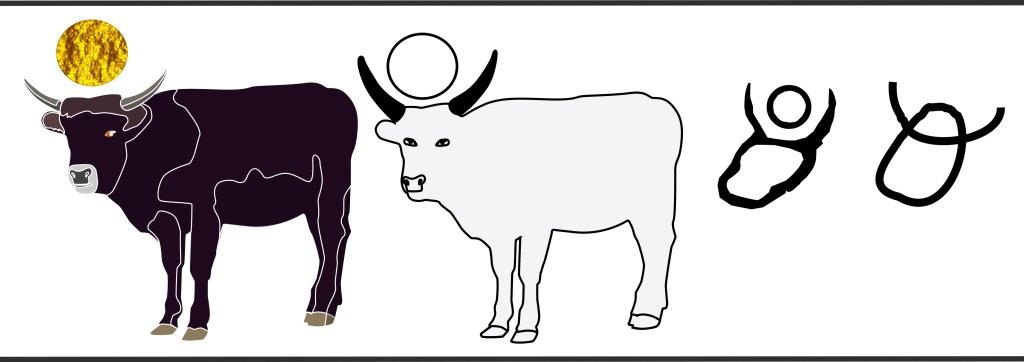
Des artistes aux besogneux
Plus de lecteurs, cela impose un surcroît de production que l’on satisfait en passant du codage en dur à une syntaxe douce, qui sera inscrite sur les murs, les tablettes et les papyrus.
Cela ne s’est pas fait sans heurter certaines sensibilités.
Le détournement des artisans de pointes et de burins, ces experts funéraires qui gravent la pierre ou enluminent les murs des temples, tombeaux et sarcophages, est contre-indiqué si l’objectif est de dupliquer les cours d’histoires, remplir les listes des courses, des entrepôts militaires ou des rôles d’imposition.
Le changement que nous supposons aurait eu lieu pendant l’une des premières périodes dites « intermédiaire », un moment long de réunification visant à se relever d’un précédent déclin. Assis sur leurs positions, il s’est trouvé des scribes chenus, qui bien que nettement moins âgés que leur culture écrite, se seraient montrés peu enclins à la simplification, redoutant d’être relégués au rang de simples copistes, des scribouillards en somme.
Extension du domaine de l’écrit.
Entre – 2 300 et – 1700, après l’apogée des grandes pyramides de Guizèh, l’économie Égyptienne a subi un long affaiblissement. Il n’est plus alors question de continuer à faire dans le grandiose et le pouvoir s’étiole au point que des « étrangers » finiront par s’emparer de la Basse-Egypte tandis que la Haute Egypte deviendra une terre d’affrontements entre factions rivales.
Pendant les temps troublés il reste des tombes, plus modestes, à creuser et à décorer avec les instructions à suivre pour franchir les épreuves post-mortem.
L’écriture hiéroglyphique reste la pratique sacrée, réservée aux occasions religieuses, sous terriennes, car la mort reste un investissement à long terme même au cours de périodes étiques.
Au fil des troubles, un chef se montre plus fort que les autres, des forces vives s’unissent, les batailles distinguent des tendances et une famille légitime se révèle et se revendique de Rà et de Horus.
Survient alors la question que tout gouvernement nouveau doit se poser : comment améliorer les choses pour éviter un nouveau déclin ?
L’Égypte a toujours tenté d’être un état centralisé et promotionnel. Un Pharaon, ou sa mère, réfléchit de façon pragmatique et personnelle : »en donnant aux castes moyennes l’écriture, vais-je conforter ma survie dans l’au-delà ? ».
Cela mérite examen.
La réponse est oui ! Dans le contexte d’un pays qui se redresse, un grand nombre de professions intermédiaires trouveraient injuste qu’un outil pratique et durable reste l’exclusivité des confréries de hauts rangs, alors que le moyen peuple est disposé à en profiter.
Ecrire plus veut dire plus de lecteurs !
Premier argument favorable : la culture cela ne se refuse pas. Cela occupe les gens quand ils ne sont pas aux champs ou sur les chantiers. Il est important qu’une partie utile de la population sache lire, surtout ce qui glorifie Pharaon.
Le second argument favorable est de notoriété publique : Pharaon veut que son peuple l’apprécie . Il n’a pas envie que son tombeau soit pillé et son nom martelé.
Il recourt probablement à la tactique immémoriale des dirigeants d’Égypte : favoriser l’accès aux responsabilités à un nombre de méritants issus du vulgaire.
Des expériences fâcheuses ont démontré que les enfants de l’aristocratie se sentant moins redevables envers leurs souverains ou brusquement agités d’ambitions désinhibées, n’étaient pas faciles à gérer.
Prosaïquement, cette écriture nous est connue comme le linéaire simplifié, apparemment parce qu’elle se trace avec des lignes.
Ce mode un peu négligé est jugé assez correct pour les échelons subalternes. Les scribes l’utilisaient lorsqu’ils étaient pressés et se contentaient d’un travail sommaire.
La délégation du savoir, depuis les grands détenteurs vers la multitude des petits utilisateurs devient facile. L’écriture bâclée des premiers devient l’expression normalisée des seconds.